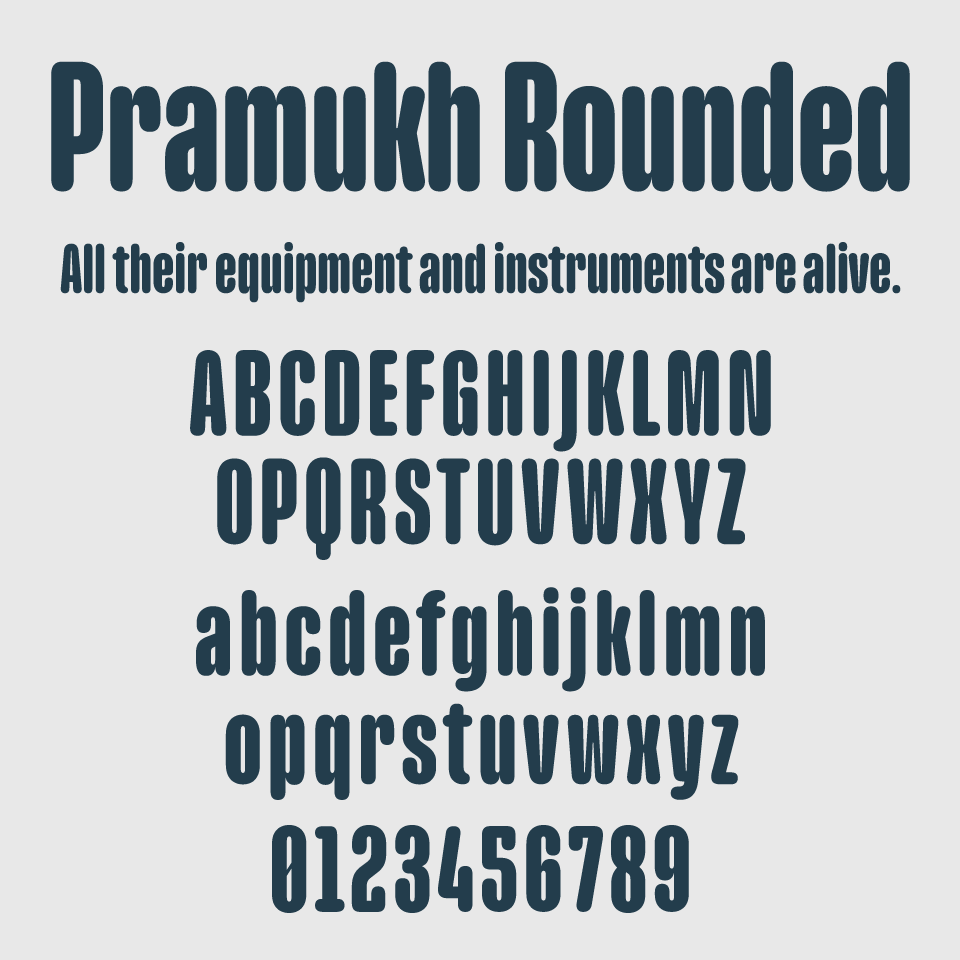
Pramukh Roundedは、直線と角をすべて丸めたような、独特の“ころん感”が特徴のラウンドサンセリフフォントです。
長体フォルムに加えて、全体に太さがありながら、角を削ることで硬さが消え、無機質になりすぎない絶妙なバランスが取られています。どこか90年代のテック感もあり、レトロフューチャー的なニュアンスも感じさせるデザインです。
ロゴやインターフェース、プロダクトのラベルなどに使うと、安心感と遊び心の両方を演出できます。情報を強く伝えながらも、どこか丸みを帯びた優しさを保つ、愛嬌のあるフォントです。
ウェイトも16スタイルあるのも嬉しいポイントです。